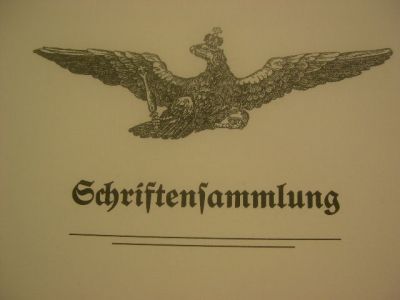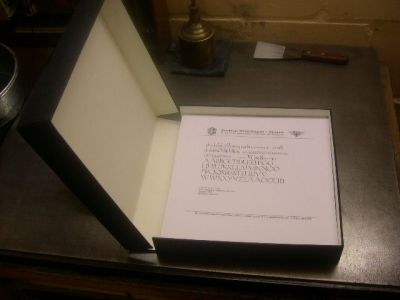
Bitte um professionelle Empfehlung
Ich erstelle seit nunmehr rund einem Jahr im Buchdruck eine Mini-Auflage mit 25 Exemplare einer Bleisatz-Schriftensammlung. Mittlerweile sind 185 von geplanten 200 Mustern fertig.
Die Drucke im Format 30 cm x 30 cm zeigen einen vollständigen Zeichensatz der jeweiligen Schrift sowie, in einer Legende, Name, Schriftgießerei, Erstguß-Jahr und Künstler dieser Schrift.
Parallel zeige ich Fotos (später Scans) aller Schriften auf meiner Webseite. Dort sind die Schriften nach DIN 16 518 klassifiziert.
Neben den letzten 15 Mustern fehlen mir noch drei Teile:
1. Eine Liste mit Korrekturen.
Rund ein Dutzend der Schriften konnte ich mit Hilfe anderer Typographen erst nach dem Druck klassifizieren. Diese hießen zunächst Typi Incogniti (mangels einer besseren Idee).
Dazu haben sich tatsächlich einige Satzfehler eingeschlichen.
Und ein paar Jahreszahlen sind falsch.
Deshalb soll eine Liste beigelegt werden.
2. Zwischenblätter mit Namen der einzelnen Gruppen.
Die DIN 16 518 besteht aus zehn Gruppen, wobei die Gruppe X, das ist die der Gebrochenen Schriften, noch einmal in a-e unterteilt ist.
Jede Gruppe und Untergruppe soll einen eigenen Zwischentitel bekommen. Darauf wird nur der Name der Gruppe gezeigt und einige typische Lettern dieser Gruppe mit Ober- und Unterlänge.
3. Ein Vorwort.
Zweispaltig, gesetzt aus einer 14 p Weiß-Antiqua. Hier möchte ich über Sinn und Zweck der Schriftensammlung schreiben und kurz den Zusammenhang im Namen des "Preußischen Bleisatz-Magazin" zwischen den Begriffen Preußen und Bleisatz erläutern.
Die Gestaltung all dessen habe ich soweit schon im Kopf.
Was mir fehlt - und hier bitte ich um konkreten Rat bzw. Empfehlung:
Zumindest das Vorwort kann ich nicht im Handsatz setzen.
Ich brauche eine Layout-Setzerei, die einen von mir gelieferten ASCII-Text nach meinen Vorgaben in 14 p Weiß-Antiqua umbricht und mir davon einen Andruck erstellen kann - einen Barytabzug. Daraus kann ich mir dann ein Klischee ätzen lassen und das dann drucken.
Ich brauche zumindest eine Setzerei, für die Begriffe wie Ligaturen kein Fremdwort sind. Dazu sollten sie, wenn es das überhaupt heute noch gibt, über das Lang-s verfügen. Die Regeln dazu auch anwenden können.
Wenn es einen solche Layout-Setzerei vielleicht sogar im Düsseldorfer Raum gibt, wäre das optimal.. obwohl.. ist das wirklich wichtig? Ich weiß es nicht. Eventuell - aber da bin ich noch unschlüssig - würde ich als eine Art Brückenschlag zwischen dem Bleisatz und der Modernen Typographie auch mit denen darüber sprechen wollen, ob sie die Zwischentitel setzen.
Ohne genau zu wissen ob es das ist was du suchst...
Soweit ich weiß haben sie die Weiß Antiqua als Hausschrift (daraus begründet sich dann meine Vermutung dass sie sich damit auskennen). Vielleicht kannst du Kontakt mit den beiden netten älteren Herren aufnehmen und direkt nachfragen.
In meinem Umfeld ist mir nur folgende Institution bekannt, welche vielleicht Deinen Anforderungen entsprechen könnte:
Liebe Kollegen der gestaltenden Zunft,
ich glaube, hier liegt ein Mißverständnis vor.
Die meisten Lieferanten für Handsatz und Maschinensatz in Deutschland und auch im Ausland kenne ich wahrscheinlich.
Was ich jetzt jedoch suche, ist eine (hoffentlich sage ich das jetzt richtig): Fotosatz Layout-Setzerei. Oder halt eine andere Möglichkeit, einen 14 p Mengensatz aus einer Weiß-Antiqua zu bestellen und als Papierabzug geliefert zu bekommen. Mir ist auch ein Mac-Typograph recht.
Die Weiß-Antiqua gibt es doch sicher als digitalisierten Font.
Und irgendein Typograph wird diesen Font besitzen.
Dem will ich ASCII-Text schicken.
Er bereitet mir dann den Text auf.
Und läßt ihn für mich irgendwo ausbelichten.
Schickt mir den Fotoabzug.
Davon lasse ich mir ein Klischee für den Buchdruck herstellen.
Das drucke ich dann.
So was suche ich.
Übrigens:
Hier kann man sehen, was alles zu Preußen gehörte:
Das Preußische Bleisatz-Magazin Rheinland
ist ganz links am westlichen Rande des Deutschen Reiches zu finden.
Ganz schön groß, was?
Georg Kraus
Hier kann man sehen, was alles zu Preußen gehörte:
Cetero Censeo:
Die Grenzen von 1527 müssen wiederhergestellt werden. Damals galt man als Geldriaan (Bewohner des Herzogtums Geldern) noch was.
Von Groningen bis Erkelenz und von Utrecht bis Enschede – das waren noch Zeiten, damals. :(
P.S.: Apropos Adler. Ich finde den Adler wirklich wunderschön! Aber viel weniger schön, als alle die Schriftproben, die du bisher gezeigt hast.
Wie Eric Gill ganz gut schrieb: "Letters are things, not pictures of things." Der Adler da, so schön wie er ist, ist kein Ding, sondern nur ein Bild von etwas. Deine Buchstaben aber sind Dinge, die immer noch lebendig sind. Verstehst du, was ich meine? ;-)